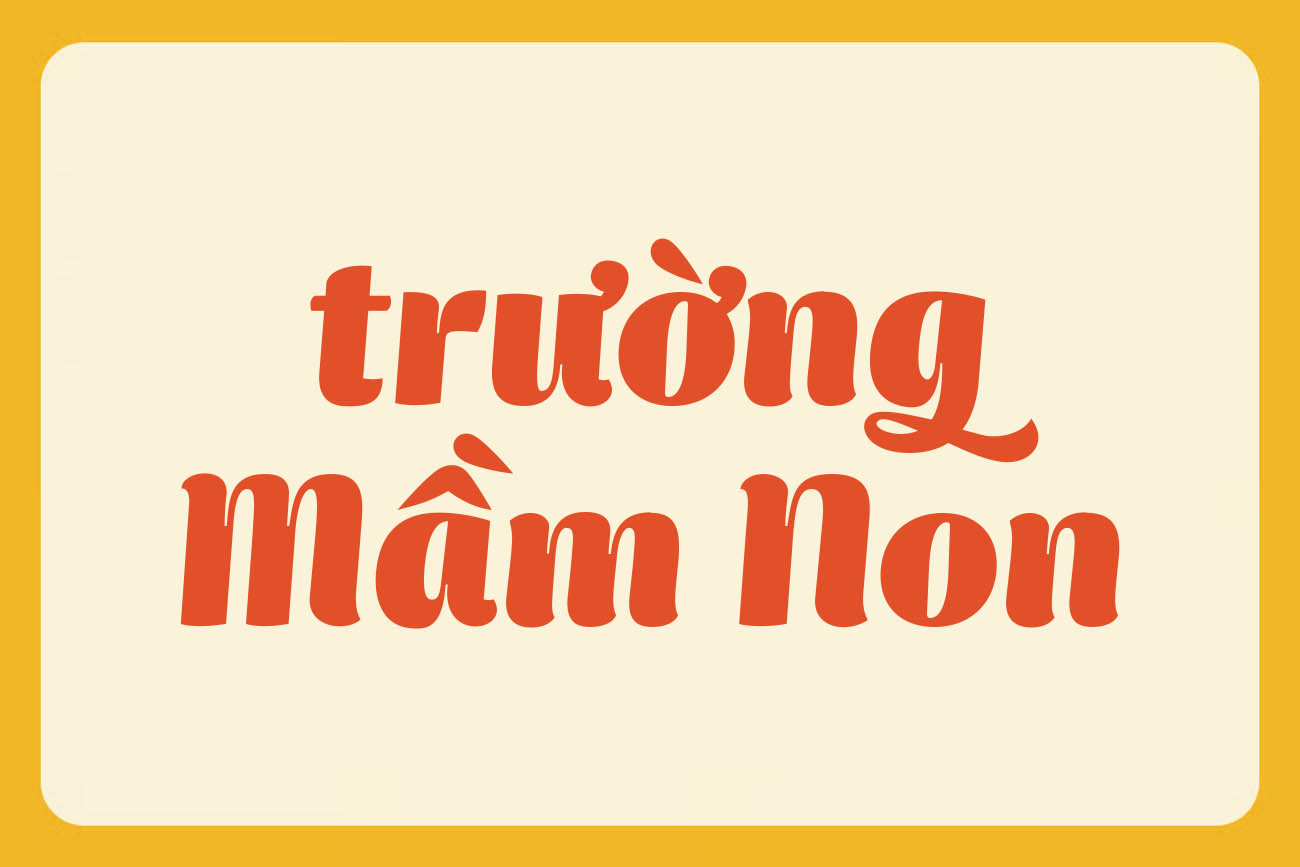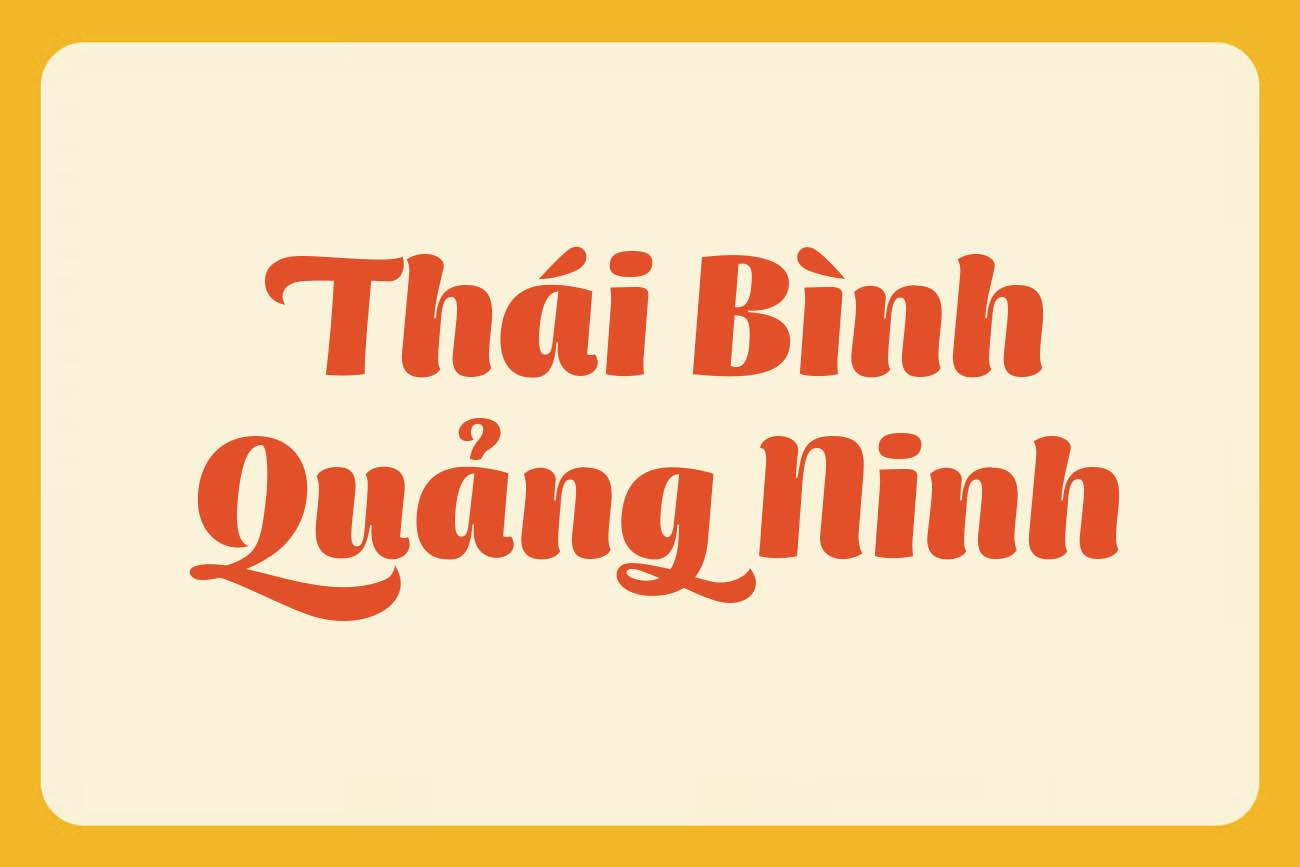
[Tải Miễn Phí] Font Chữ SVN Genica Pro Hoạt Hình Ngộ Nghĩnh, Việt Hóa Đẹp Cho Thiết Kế Trẻ Em
Tác giả Måns Grebäck
Việt hóa Team SVN
SVN-Genica Pro là một trong những font chữ hoạt hình Việt hóa nổi bật nhờ kiểu dáng bo tròn, mềm mại và đáng yêu. Với phong cách uốn lượn ngộ nghĩnh cùng tỷ lệ chữ hài hòa, font này cực kỳ lý tưởng cho các thiết kế hướng đến trẻ em, từ sách vở, bảng tên lớp đến bao bì sản phẩm học tập hoặc đồ chơi.
Tác giả & Việt hóa:
Font gốc Genica Pro được thiết kế bởi Måns Grebäck – một nhà thiết kế nổi tiếng với các bộ chữ mang cá tính mạnh mẽ và nghệ thuật. Phiên bản SVN-Genica Pro đã được STYLEno.1 Fonts (SVN Fonts) Việt hóa toàn bộ, hỗ trợ đầy đủ dấu tiếng Việt, hiển thị đẹp và không lỗi ký tự – sẵn sàng dùng cho các ấn phẩm tiếng Việt.
Đặc điểm nổi bật:
• Kiểu chữ tròn trịa, mập mạp, uốn lượn nhẹ, mang lại cảm giác vui nhộn, thân thiện – rất phù hợp với lứa tuổi nhỏ.
• Dáng chữ cao đồng đều, dễ đọc và dễ sử dụng trong nhiều định dạng in ấn và kỹ thuật số.
• Đặc biệt phù hợp để dùng làm font chữ trẻ em trong các thiết kế giáo dục, sản phẩm dành cho bé hoặc các nội dung hoạt hình.
• Font chữ Việt hóa đầy đủ, giữ nguyên phong cách gốc nhưng tối ưu để dùng trong môi trường tiếng Việt.
Gợi ý ứng dụng:
• Bìa truyện tranh, tạp chí thiếu nhi, sách tô màu
• Poster sự kiện trường học, lễ hội thiếu nhi, ngày hội gia đình
• Bảng tên lớp, học liệu mầm non – tiểu học
• Bao bì đồ chơi, sticker, quà tặng cho bé
SVN-Genica Pro không chỉ là một font chữ trẻ em đáng yêu, mà còn là công cụ thiết kế tuyệt vời cho bất kỳ ai đang tìm kiếm một font chữ hoạt hình Việt hóa đẹp – dễ dùng, sinh động và tạo cảm giác tích cực cho người xem.